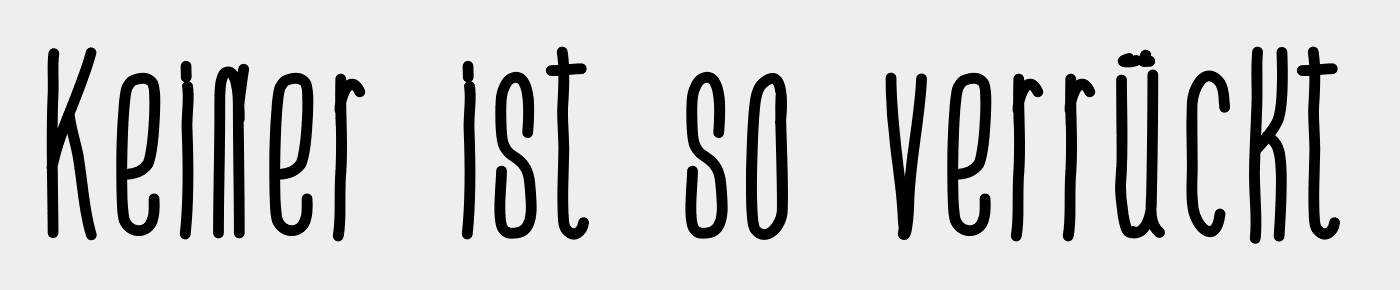
Schriftart der Einladungskarte "Love Birds" gesucht
Die beiden schauen schon ziemlich identisch aus :-). Sind auch beide von Kimberly Geswein.
Ja, die Gute hat aber auch ein ausuferndes Œuvre. Da würde ich ebenfalls die Übersicht verlieren. :-)
Nicht nur ausufernd, sondern auch hübsch anzuschauen. Sind schon feine Sachen dabei.